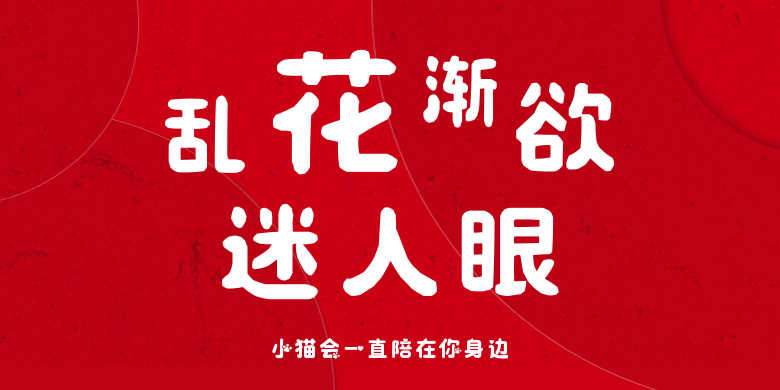
小猫会一直陪在你身边
小猫会一直陪在你身边,这款字体结构工整、笔画清晰,兼顾美观与易读性,适用于标题、正文、海报、包装、LOGO 等多种场景。字形优雅稳定,风格百搭耐看,适配日常排版与创意设计,让文字呈现更舒适、更具质感。小猫会一直陪在你身边一笔一画,皆是细节,以均衡的比例、流畅的线条打造舒适视觉体验,字形端正大气,风格简约现代。无论是商业设计、品牌宣传还是日常排版,都能轻松驾驭,让文字更有格调与力量。小猫会一直陪在你身边字体下载。